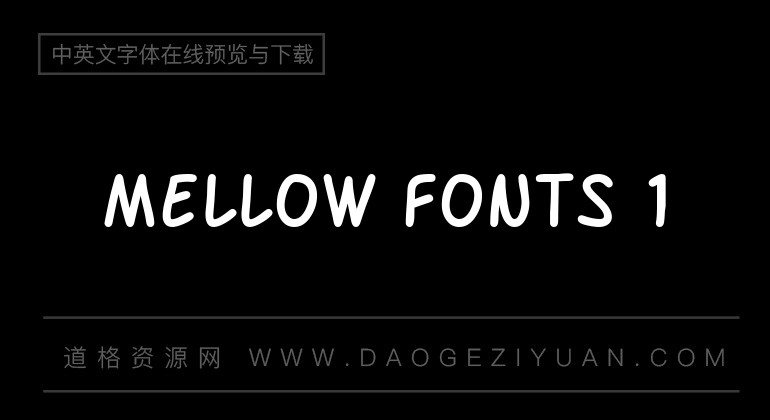
Mellow Fonts 1 字体是一款由荷兰设计师 Mellow Design Lab 创作的字体,它有着简洁优雅的设计风格,可以为您的文字设计提供精致的外观。Mellow Fonts 1 字体具有良好的可读性和可视性,可以使您的文字设计更加美观大方。此外,Mellow Fonts 1 字体还支持多种语言,可以满足您的不同文字设计需求。内容介绍
Mellow Fonts 1是一款非常不错的手写艺术字体,具有很好的视觉感,适合于文化类的宣传设计、商业类品牌的广告和产品包装设计以及个性化文字排版等较多场景。